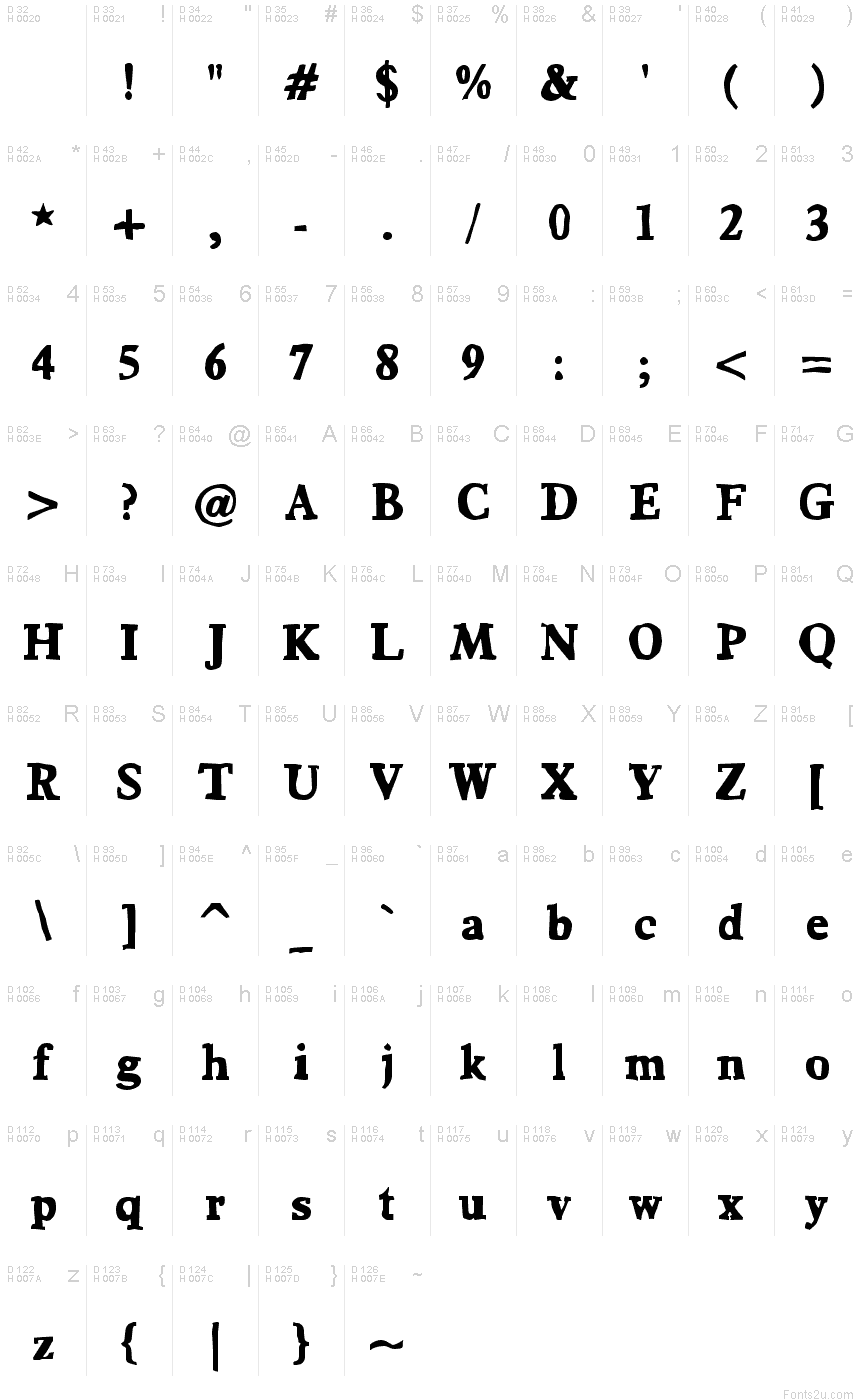
Bountiful
خط Bountiful من Surface Design Group/SDG هو خط مجاني بتصميم مزخرف (سيريف) تبدو حروفه وكأنها أزيحت عن مسارها يدوياً. تمنح السكتات العريضة والخطوط غير المتساوية كل كلمة طابعاً حيوياً ومرحاً؛ فهو خط بارز وسهل القراءة لكنه ليس جامداً أبداً. يتميز بدفء حروف الطباعة الخشبية القديمة التي طُبعت مراراً وتكراراً، مما يضفي على عناوينك نسيجاً إنسانياً وأصالةً تبعدها عن المظهر الميكانيكي الباهت.
هذا الخط المجاني يتألق عندما ترغب في أن تكون تصاميمك جريئة وودودة وذات طابع عفوي غير متكلف: سواءً للملصقات الموسيقية، المجلات المستقلة (Zines)، ملصقات البيرة الحرفية، هوية أسواق المزارعين، التغليف بأسلوب الريترو، أغطية الكتب، أو تصاميم التواصل الاجتماعي. عند استخدام Bountiful بأحجام كبيرة، تبرز تفاصيله المتموجة بوضوح؛ قم بإقرانه بخط بسيط بلا زوائد (Sans Serif) هندسي للنصوص الأساسية للحفاظ على توازن التصميم، بينما يترك لـ Bountiful مساحة لسرقة الأضواء.